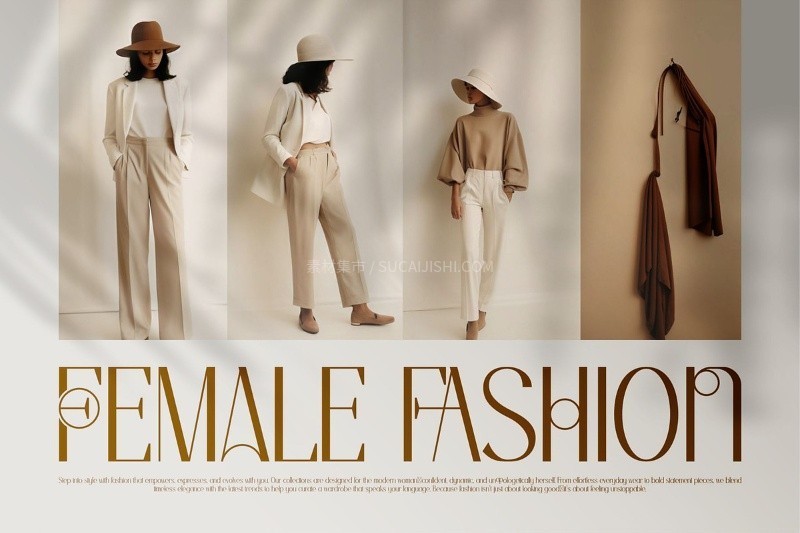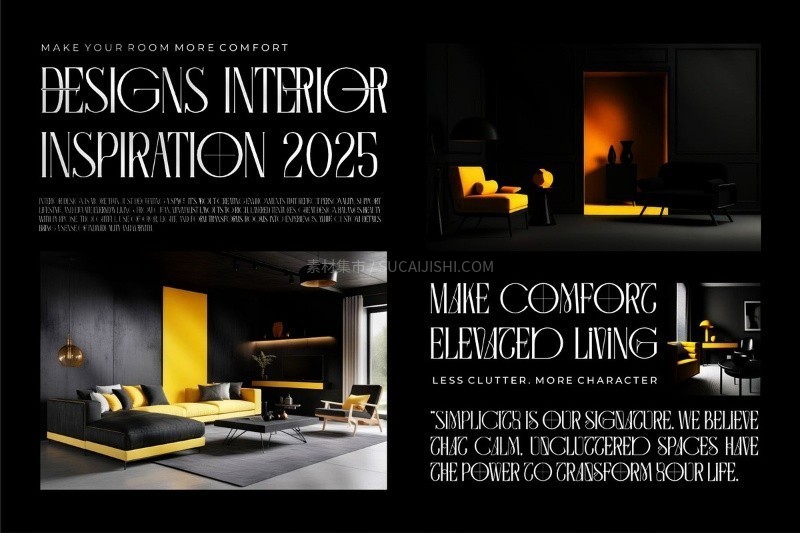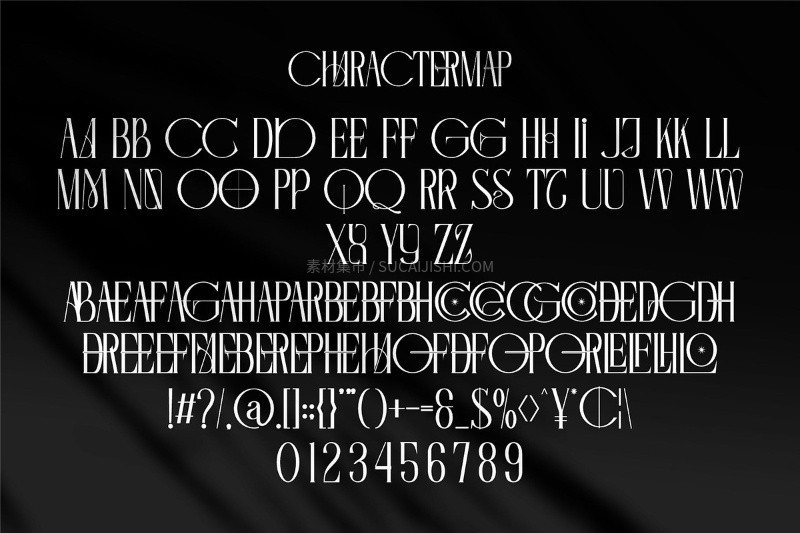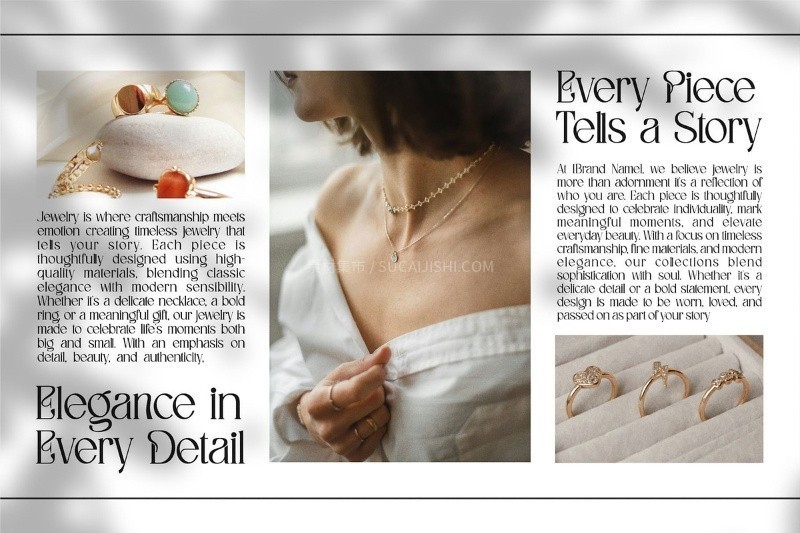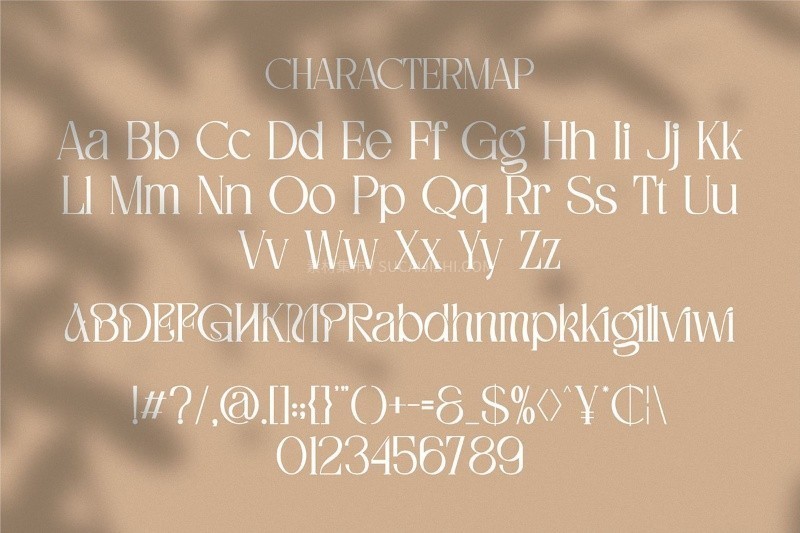
5款超有品味的英文标题衬线字体
2025 超有品味的英文标题衬线字体合集,共包含 5 款现代衬线字体,它们以其时尚、优雅、时尚的特质,彰显独特个性。这套字体非常适合与邀请卡设计、公司徽标、电影片名、名片、书名、品牌名称以及其他各种设计相结合,为您的作品注入高级质感。
Fasdeco
一款气质独特的衬线字体,它在经典衬线的基础上融入了现代的简洁感。它的笔画流畅,字形优雅,无论是作为醒目的标题还是精致的品牌标识,都能展现出不凡的品味和时尚感。
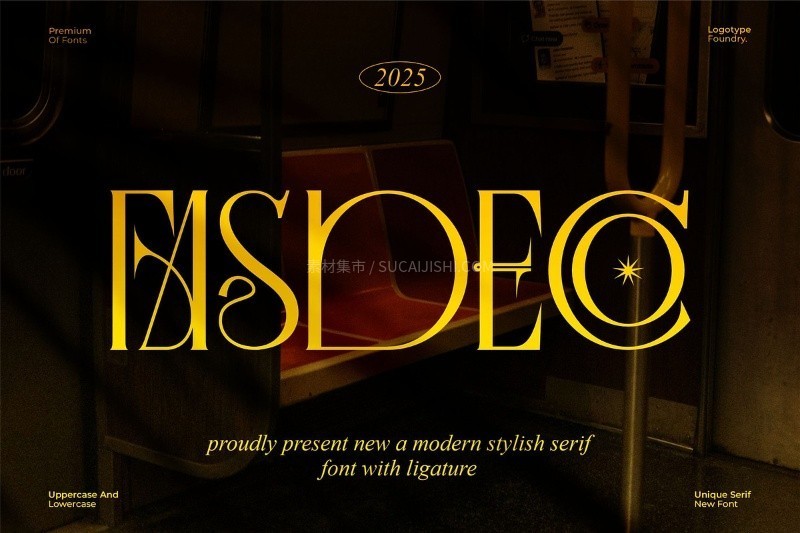
Regina
一款具有柔和曲线和温暖气息的衬线字体。它的字形更加圆润,带有一丝亲切感,同时又不失现代衬线的时尚范。Sofana 非常适合用于需要表达温馨、舒适或创意个性的设计,如邀请卡或书籍封面。
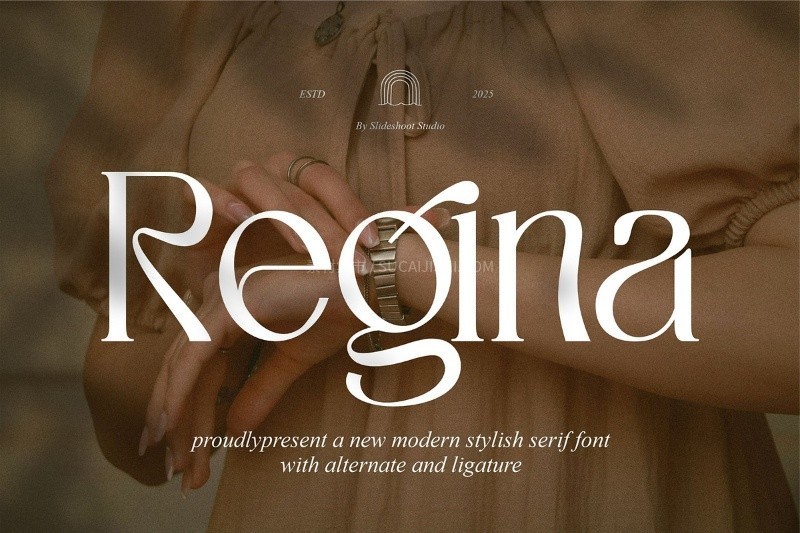
Sofana
字体以其独特的细节和微妙的变化,展现出强烈的个性和艺术性。它的结构严谨而不失灵动,能够在标题设计中制造出引人注目的焦点。Amilado 适合那些追求与众不同,希望通过字体表达品牌独特故事的设计项目。
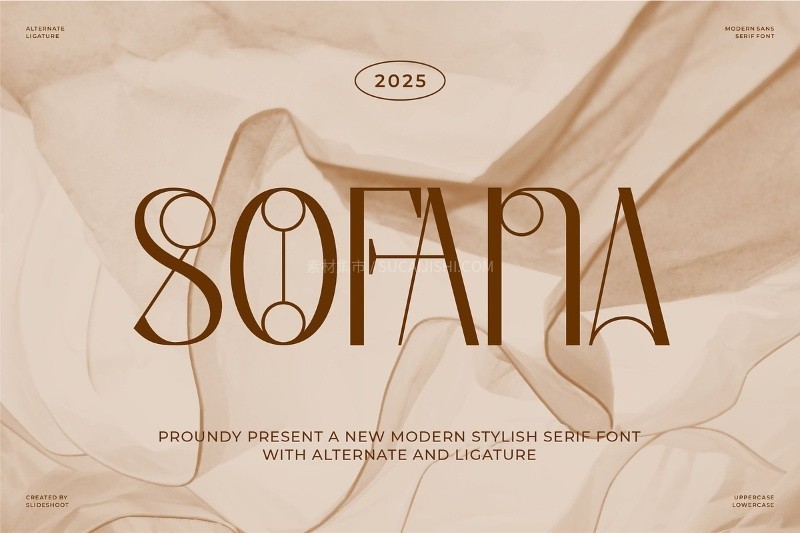
Amilado
字体以其纤细而富有力量的笔画脱颖而出。它透露着一种精致的奢华感,非常适合用于高端品牌的徽标或电影片名。Regina 的优雅气质能够瞬间提升设计的整体格调,使其更具吸引力。
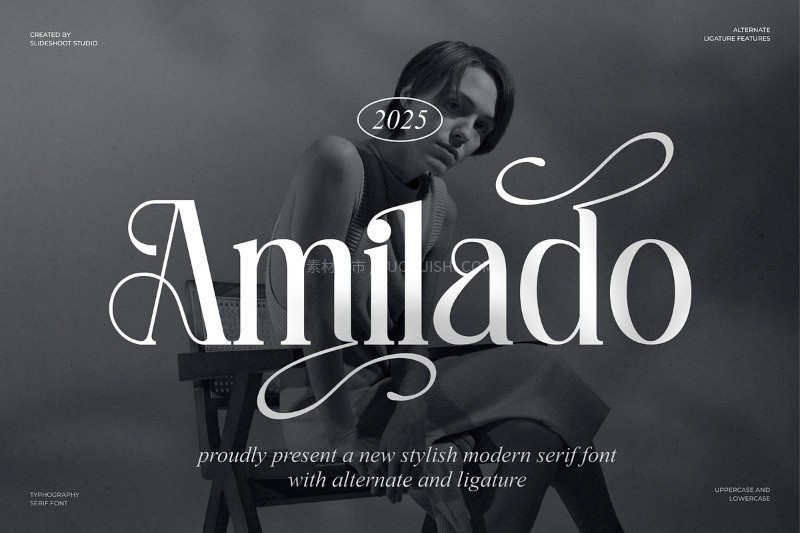
Trentia
一款结构清晰、比例和谐的现代衬线字体。它兼具经典衬线的稳重与现代设计的简洁,字形平衡而富有力量。Trentia 是公司徽标和名片设计的理想选择,能够传达出专业、可靠且不失时尚感的品牌形象。